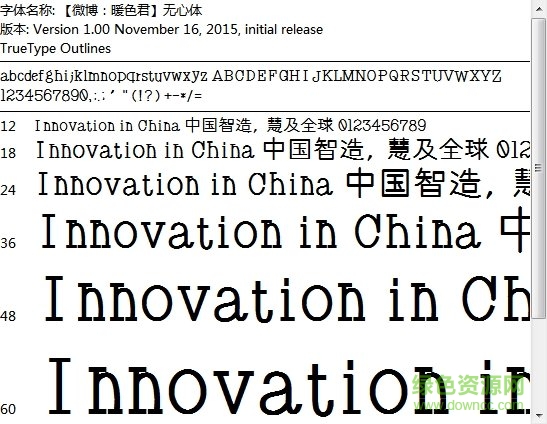
无心体是一款类似古书诗经文字的娟秀中文字体,字体颇有隶书和篆书字体结合的优美造型,给人一种十分质朴复古的精彩视觉呈现,快来绿色资源网试试吧!
无心体是微博【暖色君】推出的一款艺术字体,兼具手写字体和网页字体的特色,给人十分清爽大方的外观,字库完整,支持中英文输入,能满足大家日常生活的多种需求!
无心体是一款隶书风格的字体,字体简洁耐看,适合阅读,出自于暖色君字体系列,可用于平面设计、海报设计,包装设计等场合,也可以用于手机字体的设置,阅读效果更佳。